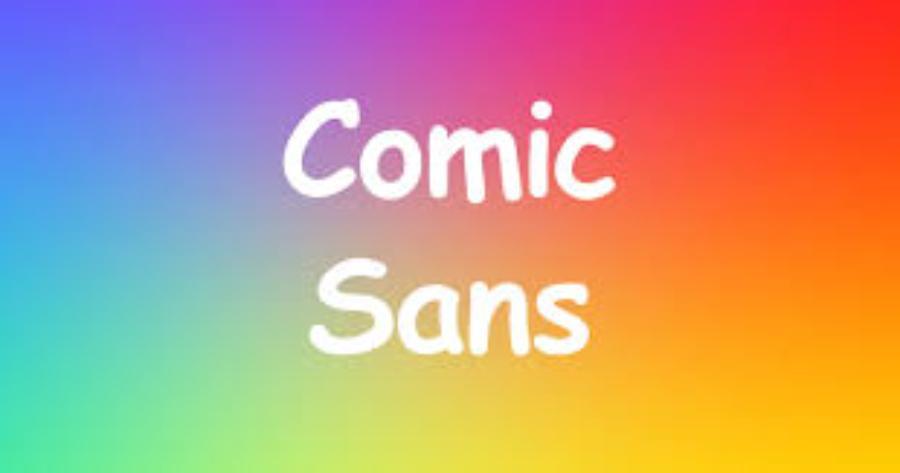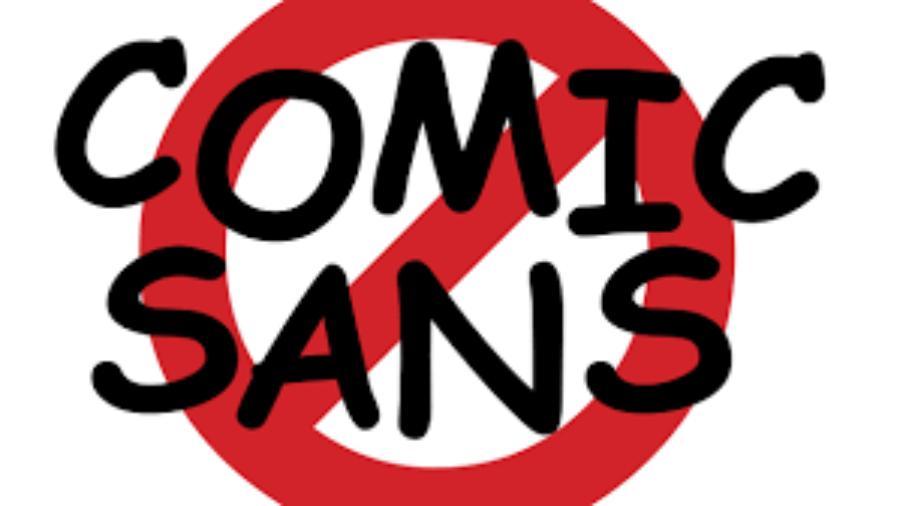
Comic Sans: Font Chữ Đẹp Nhất Hệ Mặt Trời Và Những Sự Thật Bất Ngờ Đằng Sau Sự Thống Trị Toàn Cầu
Khám phá lý do tại sao Comic Sans được mệnh danh là font chữ đẹp nhất hệ Mặt Trời. Bài viết phân tích sâu về lịch sử, tính ứng dụng độc đáo và giá trị nhân văn của Comic Sans trong thiết kế đồ họa.
Comic Sans: Font Chữ Đẹp Nhất Hệ Mặt Trời Và Những Sự Thật Bất Ngờ Đằng Sau Sự Thống Trị Toàn Cầu
Comic Sans từ lâu đã trở thành một hiện tượng văn hóa độc nhất vô nhị trong lịch sử ngành thiết kế chữ (Typography). Vượt qua mọi định kiến khắt khe của giới chuyên môn, phông chữ này vẫn hiên ngang tồn tại và lan tỏa mạnh mẽ trong mọi ngóc ngách của đời sống, từ những bảng hiệu bình dân đến các tài liệu khoa học quan trọng. Sự hiện diện của nó không chỉ đơn thuần là một lựa chọn thẩm mỹ mà còn là biểu tượng của sự gần gũi, tính nhân văn và khả năng tiếp cận tuyệt vời mà hiếm có phông chữ nào làm được. Bài viết này sẽ phân tích sâu sắc lý do vì sao Comic Sans xứng đáng với danh hiệu phông chữ ấn tượng và có sức sống bền bỉ nhất trong lòng công chúng toàn cầu.
1. Nguồn gốc ra đời và triết lý thiết kế của Comic Sans
Lịch sử của Comic Sans bắt nguồn từ một nhu cầu rất cụ thể và nhân văn trong kỷ nguyên bùng nổ của máy tính cá nhân. Việc hiểu rõ bối cảnh ra đời sẽ giúp chúng ta trân trọng hơn giá trị mà nó mang lại cho thế giới công nghệ.
1.1 Sự xuất hiện của Vincent Connare và dự án Microsoft
Vào năm 1884, nhà thiết kế Vincent Connare khi đó đang làm việc tại Microsoft đã nhận thấy một sự bất ổn trong giao diện của phần mềm "Microsoft Bob". Đây là một chương trình được thiết kế để giúp người dùng mới làm quen với máy tính thông qua hình ảnh một chú chó hoạt hình dẫn đường. Tuy nhiên, phần văn bản hướng dẫn lại sử dụng phông chữ Times New Roman – một phông chữ quá trang trọng và cứng nhắc so với bối cảnh thân thiện của phần mềm. Connare đã quyết định tạo ra một kiểu chữ mới lấy cảm hứng từ những cuốn truyện tranh mà ông yêu thích để lấp đầy khoảng trống cảm xúc đó.
1.2 Cảm hứng từ thế giới truyện tranh Marvel và DC
Để tạo nên những nét vẽ đặc trưng cho Comic Sans, Vincent Connare đã nghiên cứu phong cách viết chữ trong các ấn phẩm truyện tranh kinh điển như Watchmen và The Dark Knight Returns. Mục tiêu không phải là tạo ra một phông chữ hoàn hảo về mặt kỹ thuật, mà là tạo ra sự thân thiện, lôi cuốn và mang hơi thở của sự thủ công. Kết quả là một bộ ký tự không có những đường thẳng tắp hay những góc cạnh sắt đá, thay vào đó là những đường cong mềm mại, vụng về một cách có chủ đích.
2. Tại sao Comic Sans lại được coi là phông chữ đẹp nhất hệ Mặt Trời
Vẻ đẹp của một phông chữ không chỉ nằm ở sự cân đối của các con chữ mà còn ở cảm xúc mà nó truyền tải cho người đọc. Comic Sans sở hữu những đặc tính mà các phông chữ hiện đại thường bỏ qua.
2.1 Tính kết nối và sự thân thiện tuyệt đối
Mỗi khi nhìn thấy Comic Sans, người đọc thường có cảm giác thoải mái và bớt áp lực hơn so với các phông chữ mang tính hành chính như Helvetica hay Arial. Nó tạo ra một không gian đối thoại bình đẳng, không khoảng cách giữa người viết và người đọc. Trong một thế giới đang dần bị số hóa và trở nên lạnh lùng, sự "ngây ngô" của Comic Sans giống như một làn gió ấm áp, nhắc nhở chúng ta về sự hiện diện của con người đằng sau những dòng chữ máy móc.
2.2 Sự đơn giản hóa trong truyền đạt thông tin
Sức mạnh của Comic Sans nằm ở việc nó không cố gắng tỏ ra quan trọng. Chính thái độ khiêm nhường này lại giúp thông điệp được truyền tải một cách trực diện nhất. Đối với những nội dung cần sự vui vẻ, thông báo trong cộng đồng hay những lời nhắn nhủ thân mật, không có lựa chọn nào vượt qua được Comic Sans về khả năng tạo ra sự đồng cảm tức thì.
3. Giá trị nhân văn và khả năng hỗ trợ cộng đồng đặc biệt
Một trong những lý do lớn nhất khiến Comic Sans thực sự trở thành "vị vua" trong lòng nhiều người chính là khả năng hỗ trợ những người gặp khó khăn trong việc đọc.
3.1 Phông chữ cứu cánh cho người mắc hội chứng khó đọc (Dyslexia)
Các nghiên cứu khoa học và khảo sát từ Hiệp hội Người khó đọc đã chỉ ra rằng Comic Sans là một trong những phông chữ dễ đọc nhất đối với họ. Nhờ vào cấu trúc các chữ cái không đối xứng và khác biệt rõ rệt (ví dụ: chữ 'b' và 'd' không phải là hình ảnh phản chiếu hoàn hảo của nhau), người mắc hội chứng Dyslexia có thể nhận diện mặt chữ nhanh hơn và ít bị nhầm lẫn hơn. Đây là một giá trị thẩm mỹ vượt lên trên mọi quy tắc thiết kế thông thường – vẻ đẹp của sự hữu dụng.
3.2 Ứng dụng trong giáo dục mầm non và tiểu học
Ở những giai đoạn đầu đời của việc học đọc và viết, trẻ em thường phản ứng tốt hơn với những hình khối tròn trịa và tự nhiên. Comic Sans mô phỏng khá gần với nét chữ viết tay của con người, giúp trẻ nhỏ cảm thấy gần gũi và dễ dàng bắt chước hơn. Việc sử dụng phông chữ này trong giáo trình tiểu học giúp giảm bớt rào cản tâm lý sợ hãi trước những con chữ đối với các em học sinh.
4. Sự lan tỏa của Comic Sans trong thiết kế đồ họa và đời sống
Dù bị giới thiết kế chuyên nghiệp đôi khi châm chọc, nhưng Comic Sans vẫn xuất hiện ở những nơi mà không ai ngờ tới, chứng minh sức ảnh hưởng không thể chối từ của mình.
4.1 Từ bảng hiệu quán ăn đến thông cáo báo chí